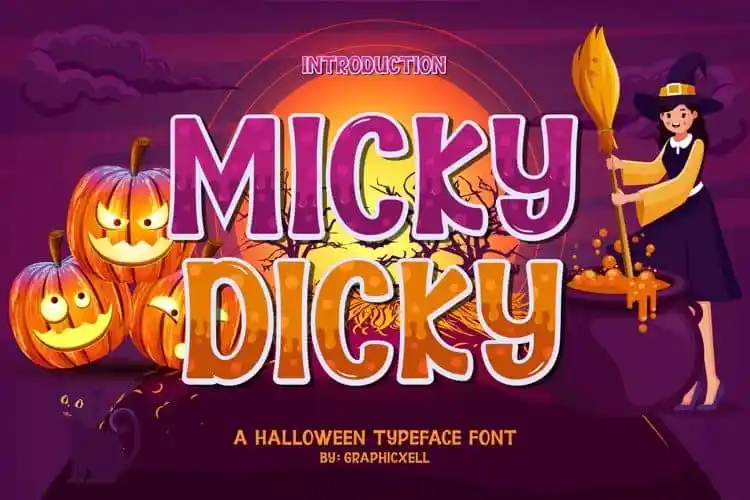
Introduzimos Micky Dicky Display Font para oferecer uma nova perspectiva no universo das fuentes display. Este design é claramente inspirado por obras que atraiam sua leitura através de um enredo intrigante e atmosfera envolvente, fazendo o espectador sentir-se fascinado, mas também desafiado. Com seu aspecto duro e autêntico, Micky Dicky Display Font transmite uma sensação clássica. Esta fonte foi projetada e compartilhada pelo designer Graphicxell, e como um tipo de display, ela se destaca e é perfeitamente apropriada para qualquer projeto especial. Ideal para produtos variados como festas de Halloween, embalagens de produtos, frases, designs de produto, trabalhos de arte em crafts, etiquetas, fotografias, marcas de água, camisetas, logos e marca. Se você estiver usando software que suporta OTF (OpenType), como Adobe Indesign, Adobe CS Illustrator, Adobe Photoshop CC ou Corel Draw, poderá acessar este design inovador. Micky Dicky Display Font é uma opção perfeita para quem busca um visual único e atraente em seus projetos gráficos.